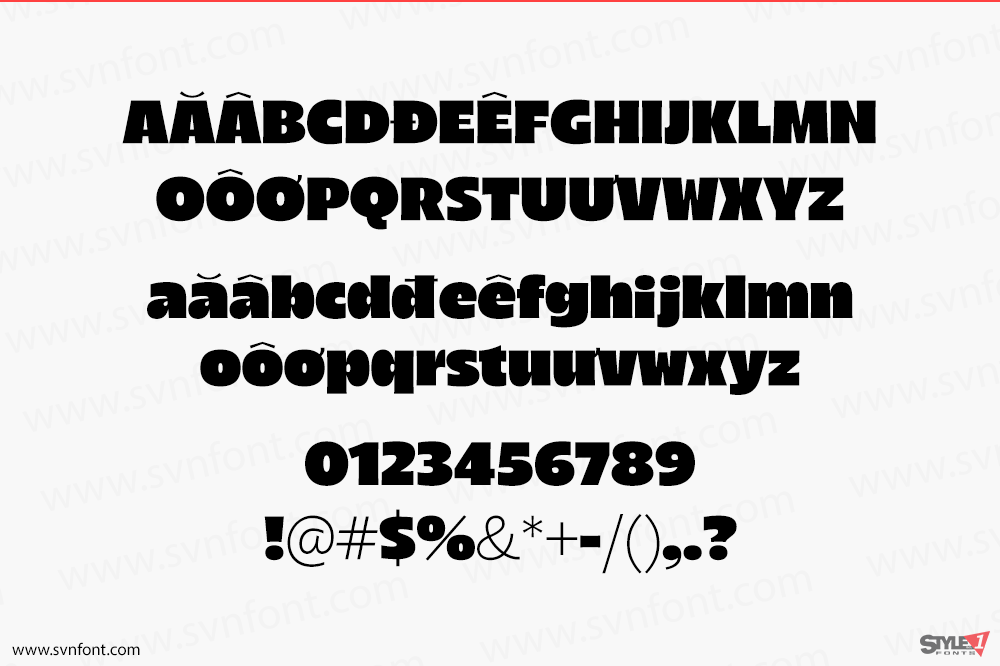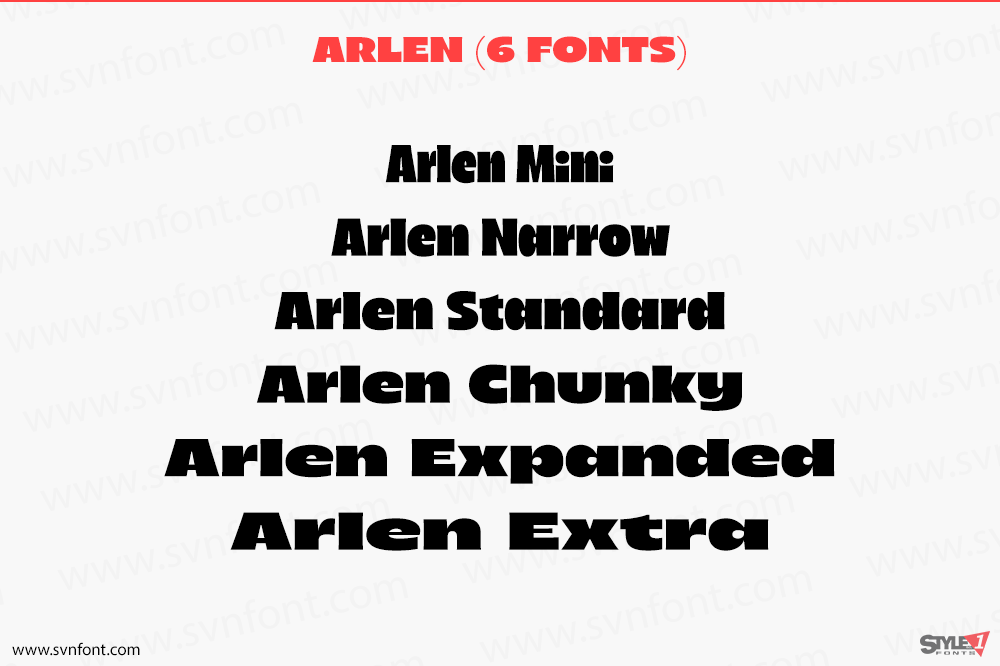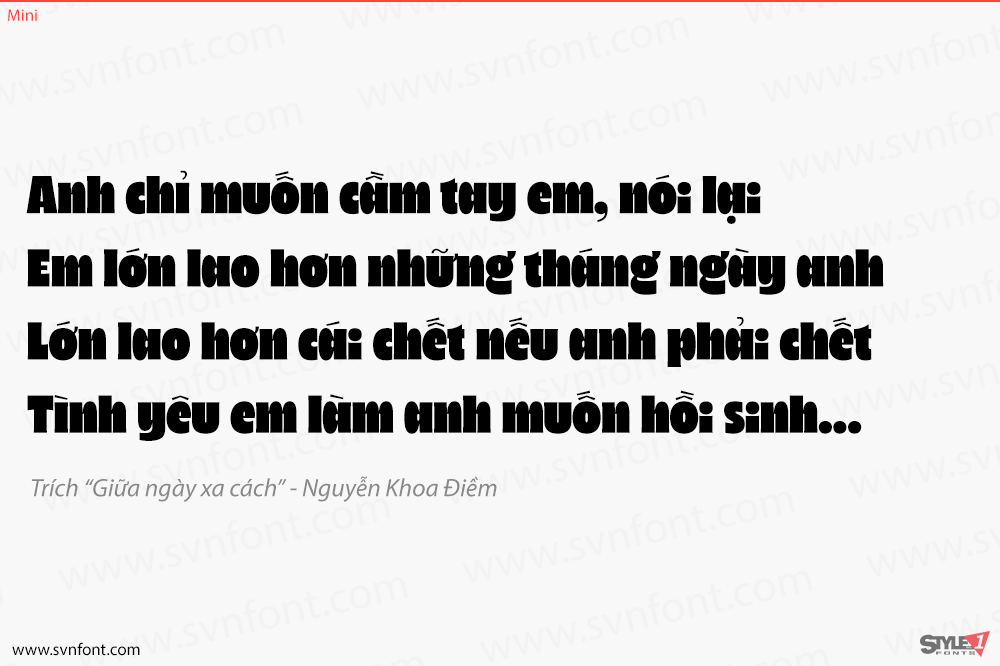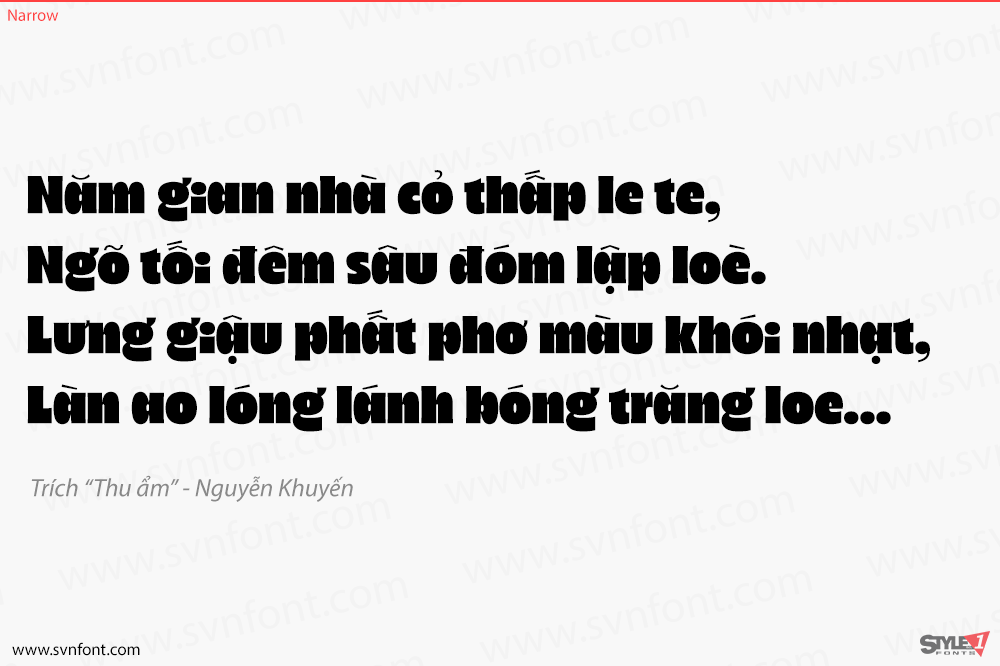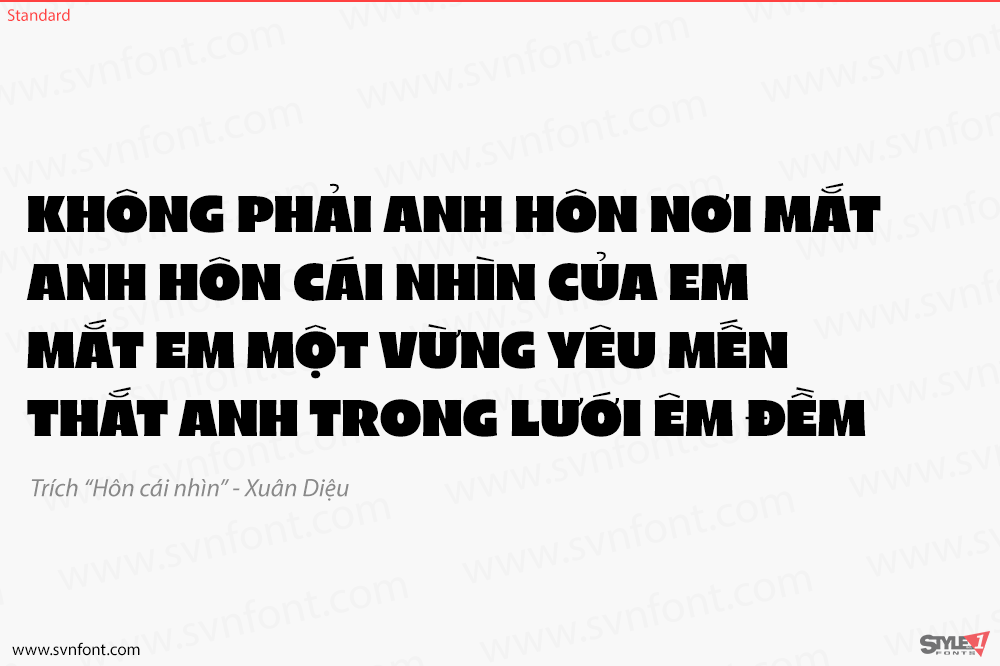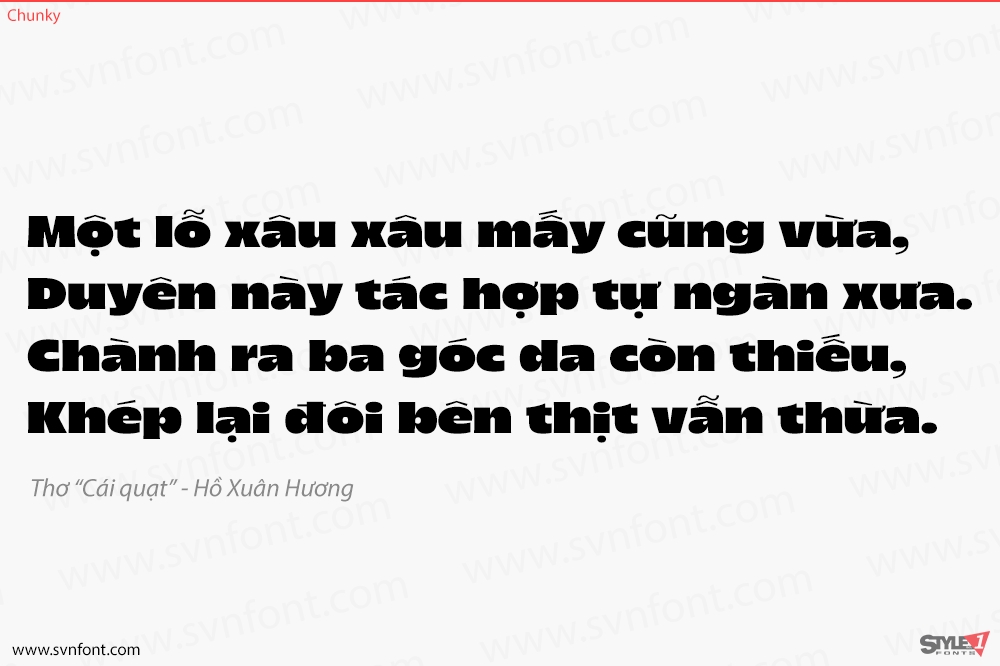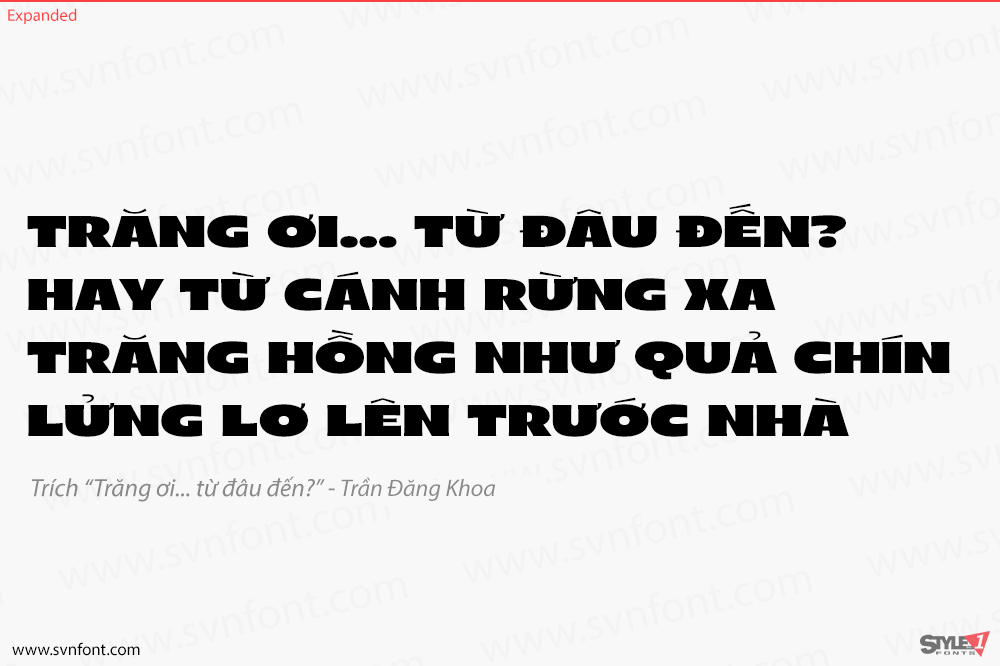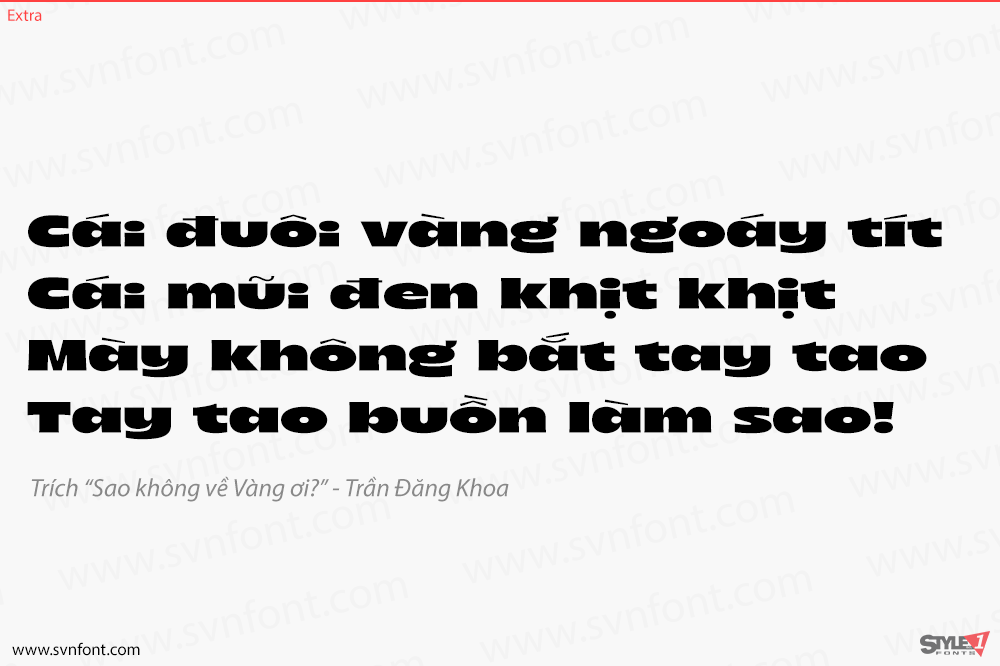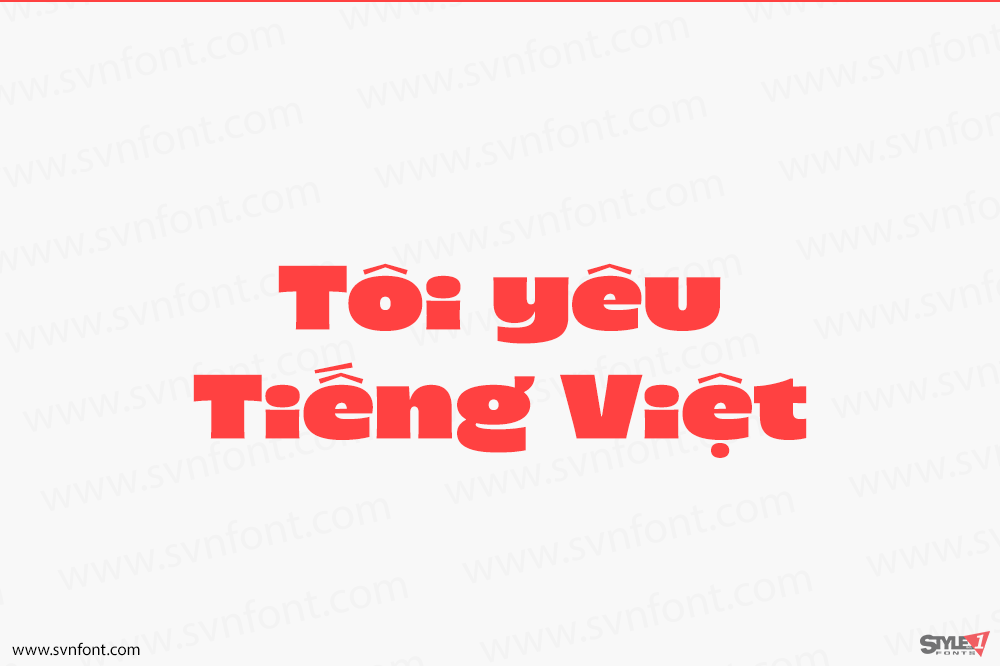
Khái niệm về TT Arlen đã phát triển từ một bản phác thảo nhỏ thành một bộ phông chữ đầy đủ với độ tương phản mạnh, khoảng cách giữa các chữ cái nhỏ và cách trình bày trực quan độc đáo.
TT Arlen là một phông sans-serif bắt mắt, phù hợp cho việc xây dựng thương hiệu và tiêu đề. Tùy thuộc vào bối cảnh của dự án, phông chữ có thể thay đổi tính cách từ vui tươi sang tinh tế về mặt thẩm mỹ. TT Arlen dựa trên phong cách “humanist grotesque” được gợi ý bởi các nét mở và tâm trạng thân thiện. Tuy nhiên, trước hết, bộ phông chữ này thu hút người xem bằng đặc điểm trình bày (display character) chứ không phải cấu trúc của nó.
Về mặt thị giác, TT Arlen rất dễ nhận biết giữa các phông humanist grotesque khác. Các chữ cái lớn với khoảng trắng tối thiểu, các nét thân chữ được làm dày, ít tương phản giữa chữ hoa và chữ thường, và mật độ sắp xếp cao. Đồng thời, các dấu phụ (diacritics) khá tinh tế, mang lại cho bộ phông chữ này sự độc đáo. Một thủ thuật hình ảnh khác là các chữ ‘i’ và ‘j’ viết thường, nhảy ra khỏi dòng.
Nhà thiết kế: TypeType Team, Yulia Gonina, Eugene Tantsurin